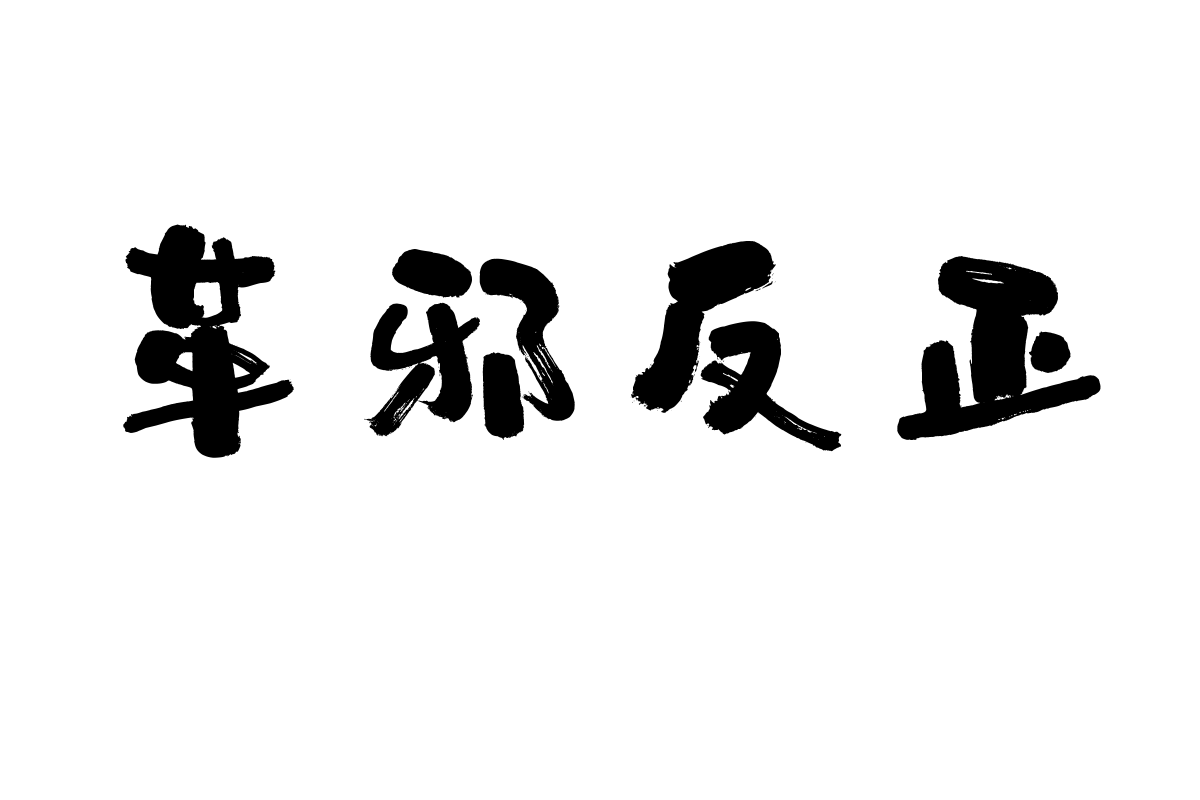
龚帆和风体是一款由龚帆设计的中文字体。这款字体具有独特的艺术风格,线条流畅,字形优美,给人一种优雅而古朴的感觉。龚帆和风体的笔画粗细不一,既有细腻的笔触,又有粗犷的线条,形成了一种独特的视觉冲击力。同时,龚帆和风体还融入了中国传统书法的元素,使得整个字体充满了浓厚的文化气息。
龚帆和风体适用于各种需要展示中国传统文化元素的场合,如广告、海报、宣传册等。它的使用可以让文字更加生动有趣,吸引人们的眼球,提高信息的传达效果。此外,龚帆和风体还具有较高的辨识度和可读性,使得文字在众多字体中脱颖而出,成为一道亮丽的风景线。